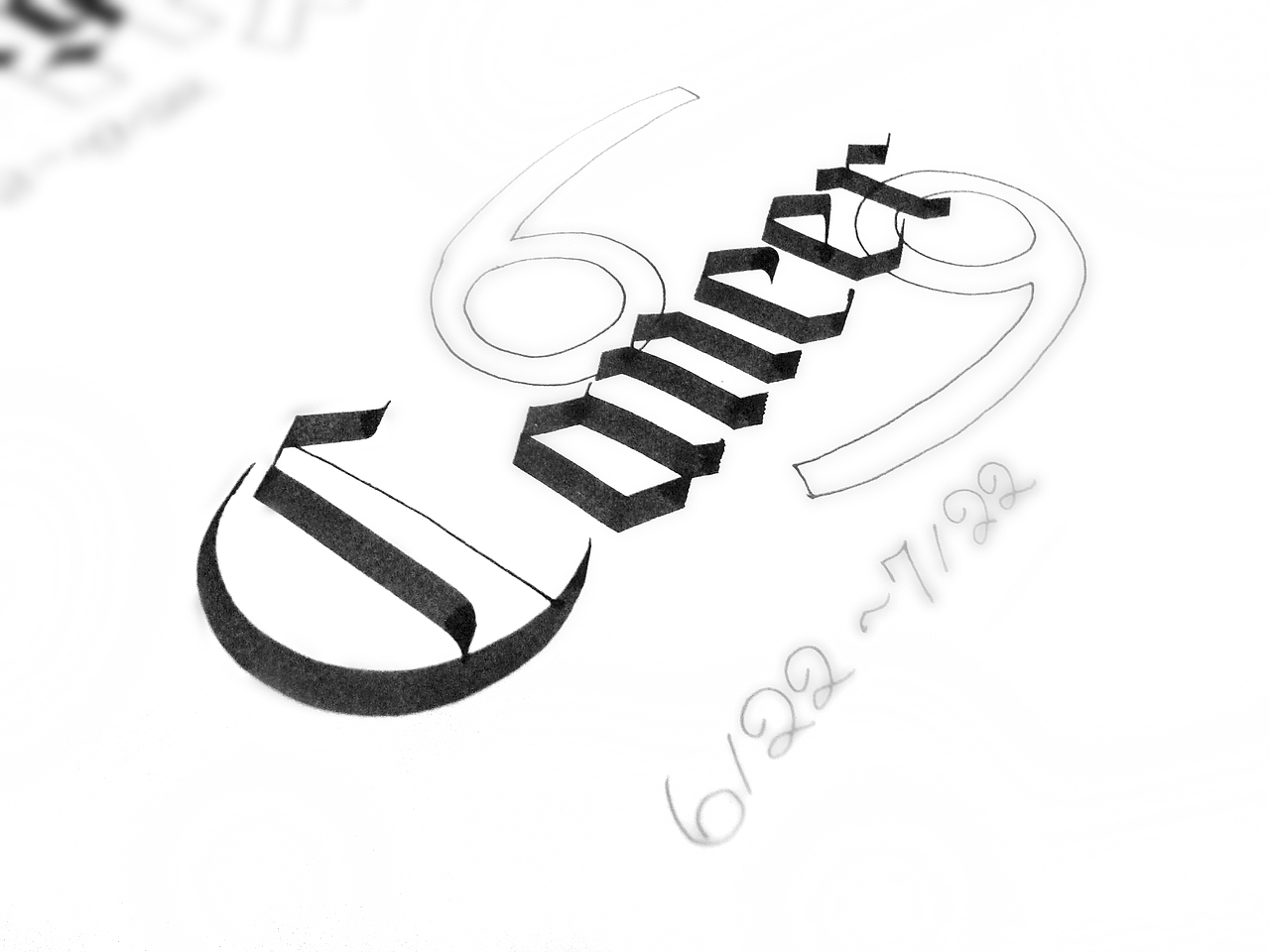
哥特12星座
星座 日期(公历) 英文名
魔羯座 (12/22 - 01/19) Capricorn
水瓶座  (01/ 20- 02/18) Aquarius
双鱼座 (02/19- 03/20) Pisces
白羊座 (03/21 - 04/20) Aries
金牛座  (04/21 - 05/20) Taurus
双子座 (05/21 - 6/21) Gemini
巨蟹座 (06/22- 07/22 Cancer
狮子座 (07/23 - 08/22) Leo
处女座 (08/23 - 09/22) Virgo
天秤座 (09/23 - 10/23) Libra
天蝎座 (10/24 - 11/21) Scorpio
射手座 (11/22 - 12/21) Sagittarius